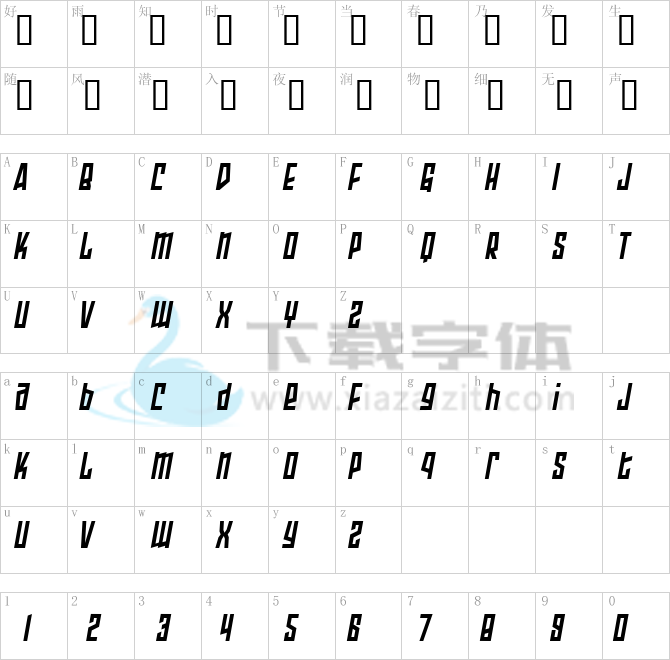
Armor Piercing 2.0 BB.ttf字体下载,这款字体结构工整、笔画清晰,兼顾美观与易读性,适用于标题、正文、海报、包装、LOGO 等多种场景。字形优雅稳定,风格百搭耐看,适配日常排版与创意设计,让文字呈现更舒适、更具质感。Armor Piercing 2.0 BB.ttf字体下载一笔一画,皆是细节,以均衡的比例、流畅的线条打造舒适视觉体验,字形端正大气,风格简约现代。无论是商业设计、品牌宣传还是日常排版,都能轻松驾驭,让文字更有格调与力量。Armor Piercing 2.0 BB.ttf字体下载字体下载。